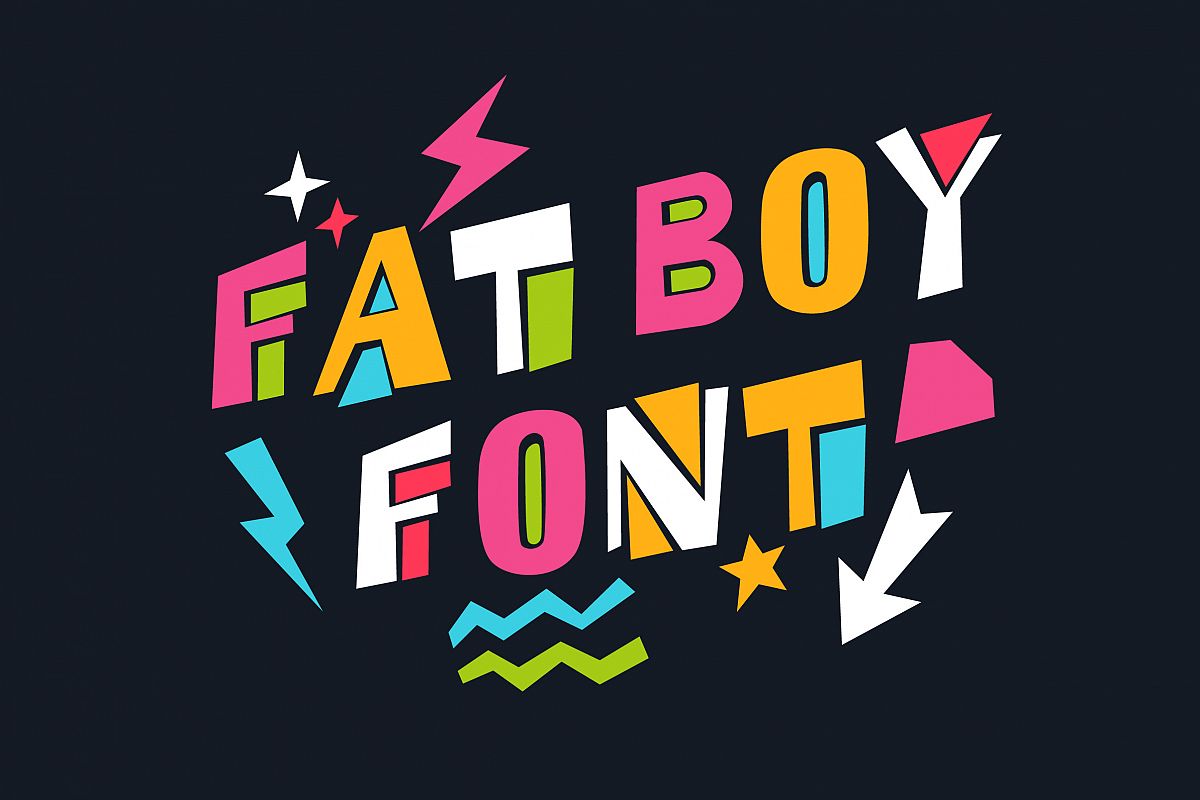
FAT BOY
Fat boy one
Fat boy two
Fat boy three
Привет, я хочу представить свой новый шрифт Fat boy. Это декоративный шрифт, который хорошо выглядит в больших размерах и небольших заголовках. Шрифт содержит латинские прописные буквы, знаки препинания, символы и цифры.